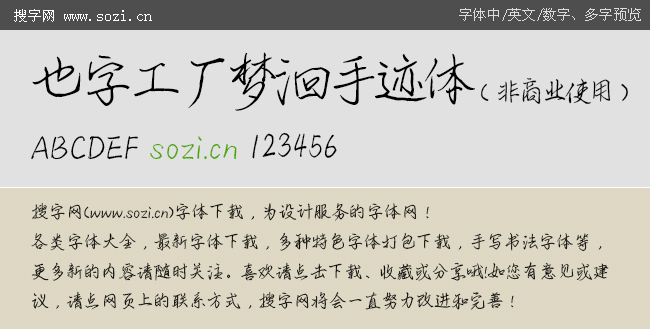
也字工廠夢(mèng)洄手跡體
搜字網(wǎng)給大家提供一款也字工廠夢(mèng)洄手跡體(非商業(yè)使用)中文字體下載,也字工廠夢(mèng)洄手跡體是一款手寫書法字體,字體書寫流暢,自然大方,具有很好的視覺效果。適合應(yīng)用于書籍畫冊(cè)、海報(bào)、網(wǎng)頁設(shè)計(jì)等應(yīng)用(此字體為個(gè)人非商用版,商用可以聯(lián)系:官方網(wǎng)址:https://yefont.com/home,聯(lián)系方式:13798980448)。